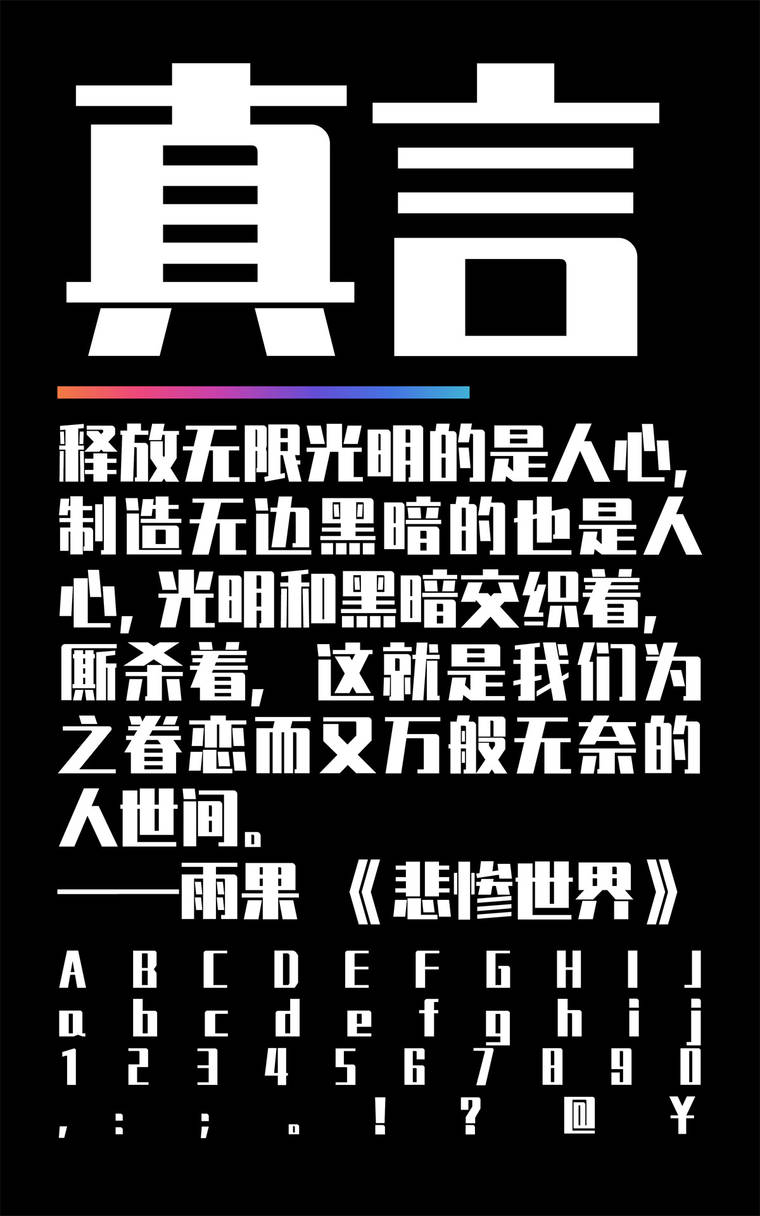
锐字真言体免费商用,这款字体结构工整、笔画清晰,兼顾美观与易读性,适用于标题、正文、海报、包装、LOGO 等多种场景。字形优雅稳定,风格百搭耐看,适配日常排版与创意设计,让文字呈现更舒适、更具质感。锐字真言体免费商用一笔一画,皆是细节,以均衡的比例、流畅的线条打造舒适视觉体验,字形端正大气,风格简约现代。无论是商业设计、品牌宣传还是日常排版,都能轻松驾驭,让文字更有格调与力量。锐字真言体免费商用字体下载。
字体特征:笔触浑厚有力,笔画曲折有度,字型个性鲜明,刚柔并济,落笔简洁有序,给人以遒劲有力、端正凝练的感觉。直角与圆角的错落搭配使得字体婉转有度,落落大方,具有自己独到的风格。